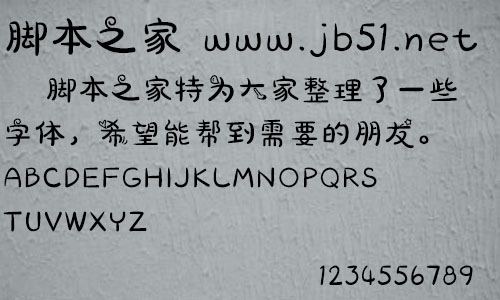
方正手跡-鴨嘴獸由方正字庫范雅瓊,李瀟設(shè)計(jì)師出品的一款藝術(shù)字體,字體筆觸粗實(shí),文字結(jié)構(gòu)靈活,筆畫錯(cuò)落有致,打破了許多固有的排列模式,適合應(yīng)用于藝術(shù)設(shè)計(jì)、平面宣傳設(shè)計(jì)、網(wǎng)頁設(shè)計(jì),書法等領(lǐng)域。
鴨嘴獸這款字,其文字結(jié)構(gòu)靈活,筆畫錯(cuò)落有致,打破了許多固有的排列模式。這款字體手寫風(fēng)格鮮明,筆形圓融渾穆,個(gè)性清新萌動(dòng),適用于兒童類品牌的廣告和產(chǎn)品包裝設(shè)計(jì)。